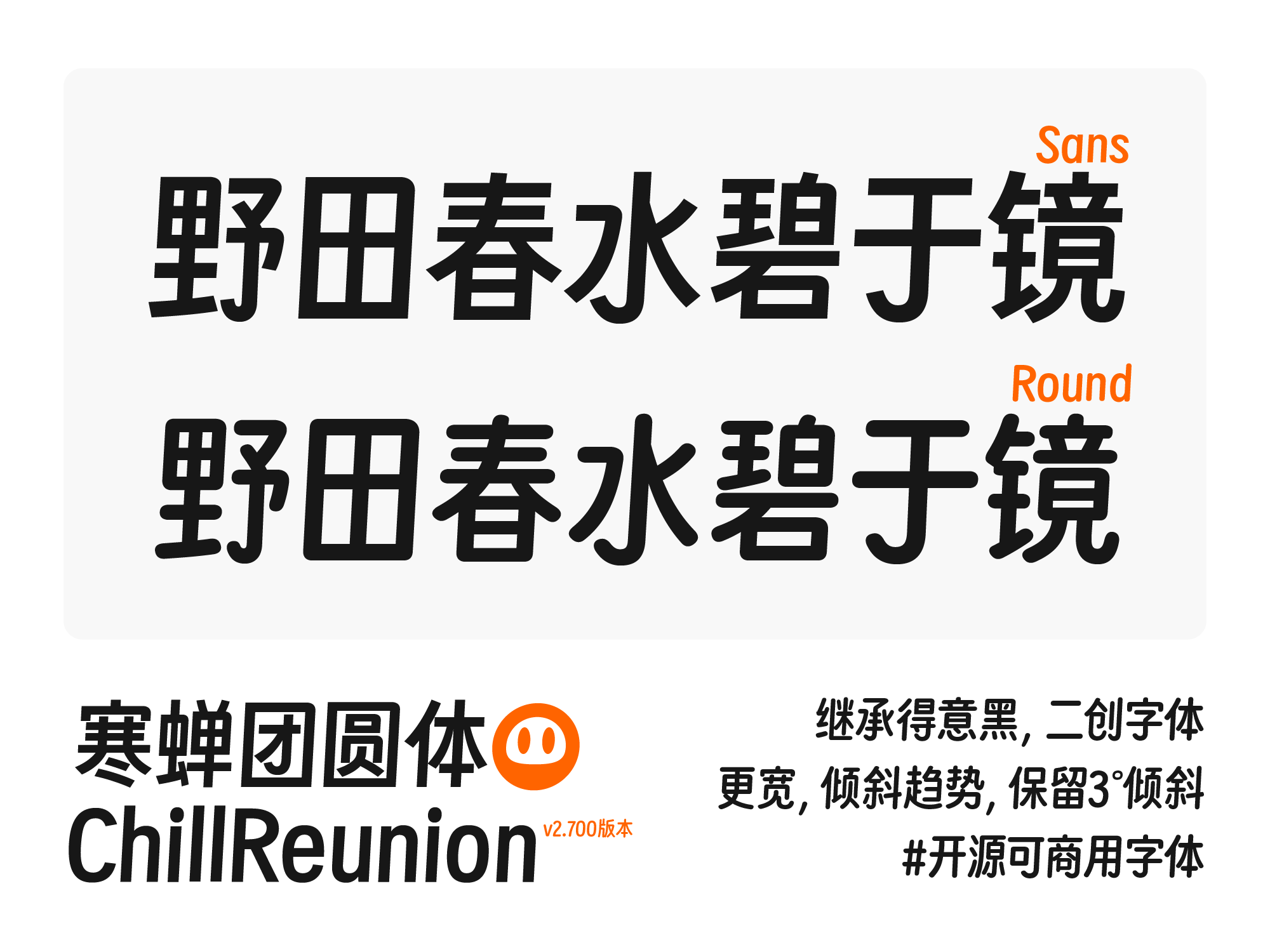
寒蝉团圆体是一款基于黑体风格进行二次创作的字体设计作品。该字体在保持黑体基本骨架与稳重感的基础上,融入了细微的动态平衡美学,整体呈现出轻微且一致的倾斜趋势,这一特征使得字形在静态中流露出一丝灵动。在当前版本中,设计者将字体的倾斜角度精确调整为3度,这一数值经过反复视觉校准,旨在平衡可读性与个性表达——既不会因过度倾斜影响长时间阅读的舒适度,又能有效打破传统黑体的呆板印象,为版面增添适度的活力与现代感。 此外,本版本进行了显著的扩展与优化。一方面,新增了若干常用及特殊字符,覆盖了更广泛的语言符号需求,增强了字体的实用性与适配性,使其能够满足多样化的排版场景。另一方面,字体对竖排特性进行了专门优化,调整了部分笔画结构与字距,确保在垂直排列时仍能保持均匀的视觉密度与流畅的阅读节奏,使竖排文本同样呈现出优雅、整齐的版面效果。这些改进共同使得寒蝉团圆体在兼具功能性的同时,也拥有独特的视觉气质,适用于标题、品牌标识、创意设计等多种用途。